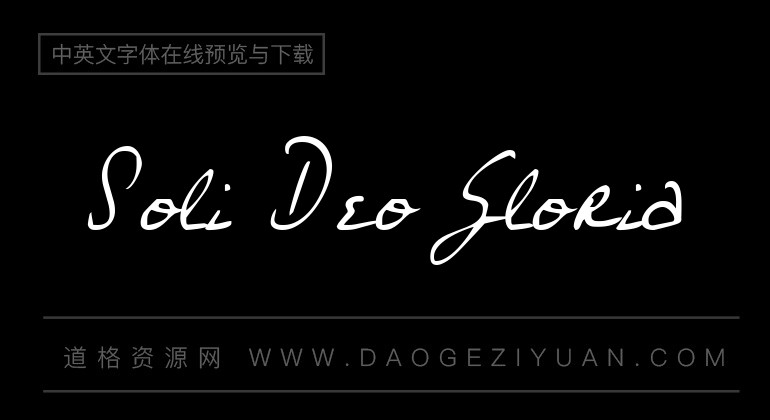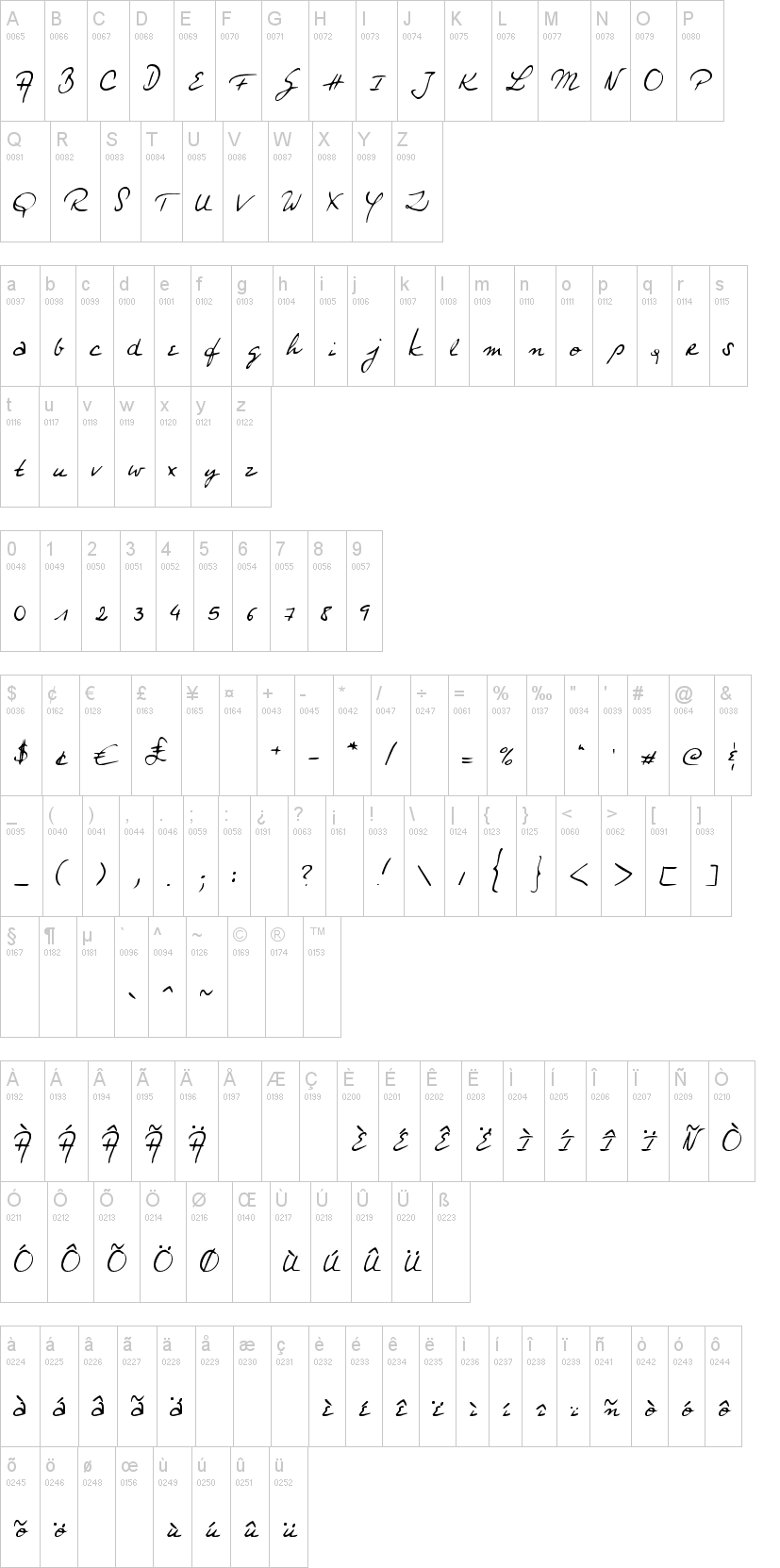
Soli Deo Gloria
Soli Deo Gloria 是一种基于拉丁字母的装饰字体,通常用于书法和印刷设计。它的名称来源于拉丁语,“Soli Deo Gloria”意为“独归上帝荣耀”,这是一个基督教信仰中的重要概念,代表着人们应该以荣耀上帝为目标,而不是追求自己的功名利禄。 Soli Deo Gloria 字体的特点是其装饰性和优美的线条,这些线条通常有弯曲、纤细和复杂的形状。该字体的设计灵感来自于17世纪荷兰文艺复兴时期的书法和印刷艺术,它在设计中融合了拜占庭文化和文艺复兴时期的艺术特点。 该字体的应用广泛,适用于印刷、海报、广告、名片等各种设计领域,其弯曲的线条和优美的字形赋予了设计作品更为精致和高雅的视觉效果。
Soli Deo Gloria是一款非常不错的手写艺术字体,具有很好的视觉感,适合于文化类的宣传设计、商业类品牌的广告和产品包装设计以及个性化文字排版等较多场景。
Soli Deo Gloria字符映射图